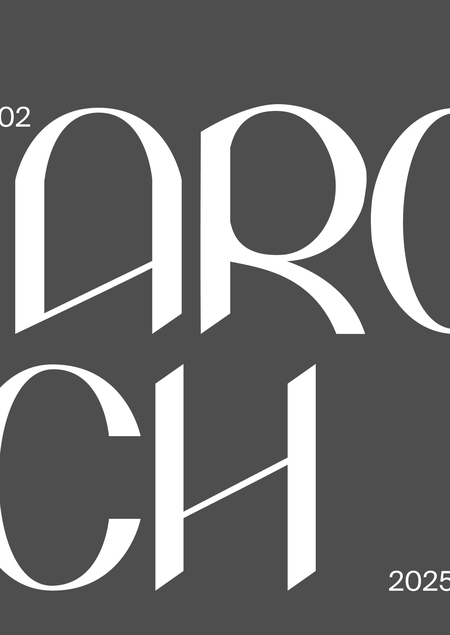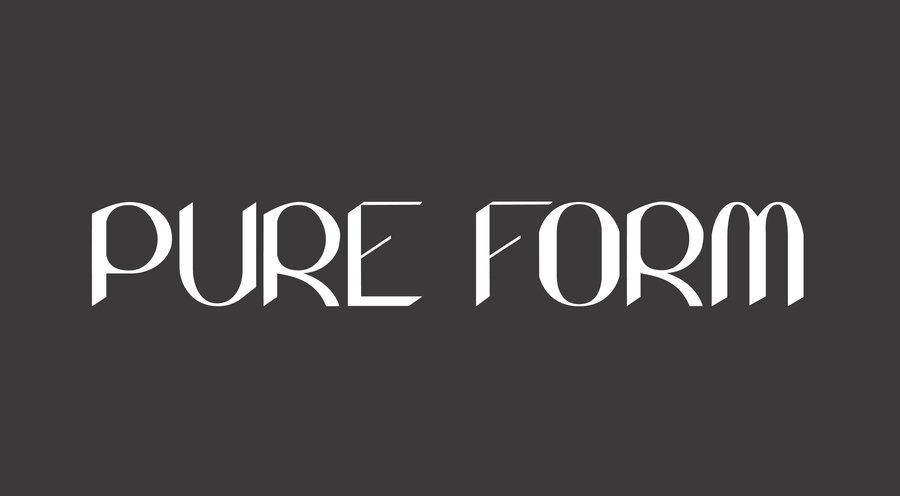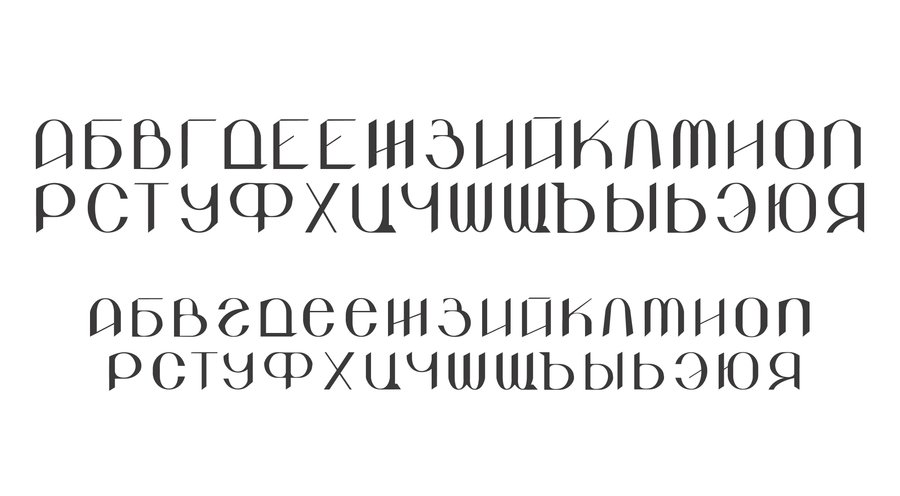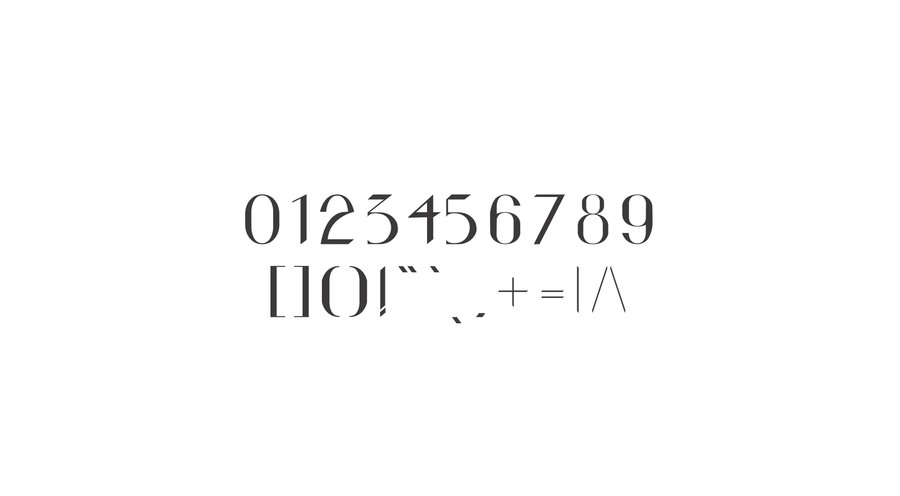
Шрифт Arch
Шрифт Arch — шрифт, который был вдохновлен адаптацией рукописного шрифта Кодекса Троянской Войны, которым я овладела на каллиграфии. ARCH — (с англ. «арка») отражает пластичность и в то же время строгость линий, широкие основания букв и зауженные элементы
касса: латиница
касса: кириллица
цифры / доп.знаки
ребрендинг для винтажного бара S’aint bar, ул. Рубинштейна, 38